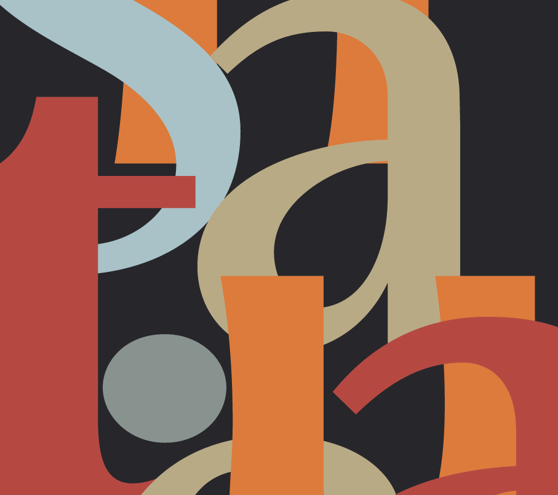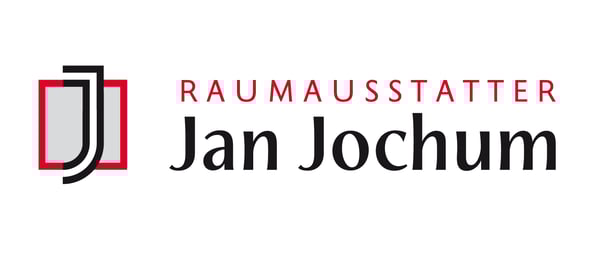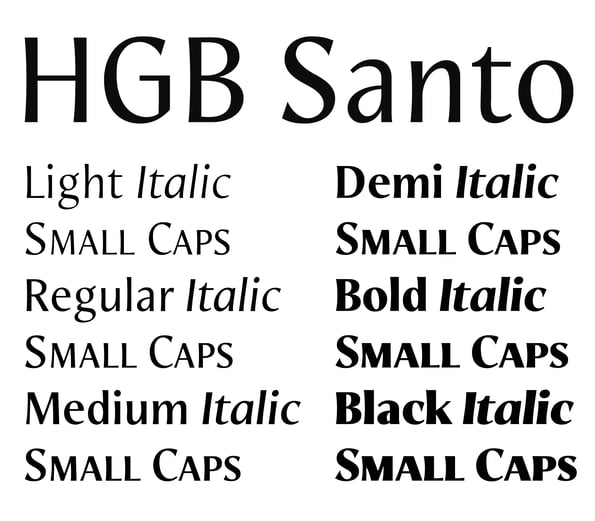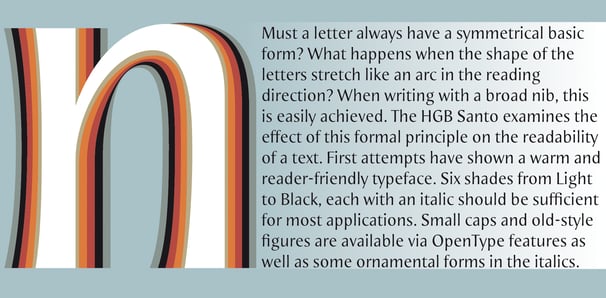
HGB Santo
Muss ein Buchstabe immer eine symmetrische Grundform haben? Was passiert, wenn sich die Form der Buchstaben in Leserichtung spannt wie ein Bogen? Beim Schreiben mit der Breitfeder ist dies ohne große Probleme zu erreichen, wie bei der »HGB Unik« zu sehen. Die HGB Santo erprobt die Wirkung dieses Formprinzips auf die Lesbarkeit eines Textes. Erste Versuche mit einer Urkunde und mit einem Faltblatt haben ein sehr lesefreundliches, warmes Schriftbild gezeigt. Sechs Abstufungen von Light bis Black mit jeweils einer Kursiven sollten für die meisten Anwendungen reichen. Über OpenType-Features sind Kapitälchen und Mediävalziffern verfügbar sowie einige Zierformen bei den Kursiven.